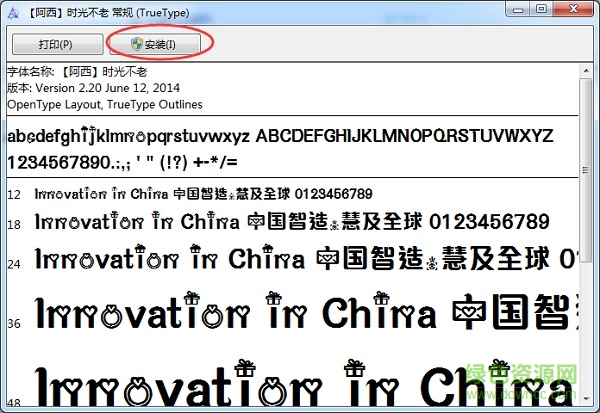
時(shí)光不老字體免費(fèi)版是一款可以在win7、win8、xp、win10操作系統(tǒng)上安裝的心形字體。這個(gè)字體非常的唯美,可以用來設(shè)計(jì)海報(bào)、廣告等。喜歡的用戶歡迎來綠色資源網(wǎng)下載使用。
時(shí)光不老字體是一款用于藝術(shù)設(shè)計(jì)方面的字體,除了簡潔美觀的字體外形還加入了記事本、日歷、心形、小禮物、信封等圖形元素,讓字體充滿活力!